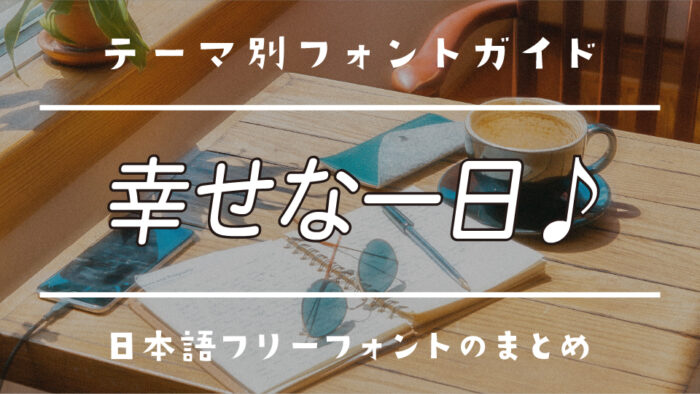
今回は、あたたかくて優しい気持ちになれる最近流行っている「幸せな一日」フォントな日本語フリーフォントをご紹介します。
Vlog風の映像やエモい字幕テキストにぴったりなフォントとして人気が高まっている「幸せな一日」フォントは、まるくて素直な印象の丸ゴシック体。ちょっとした日常の尊さや、心がじんわりとする瞬間を表現する際にぴったりあフォントです。
今回は、そんな「幸せな一日」に似ている近しい、やさしくてナチュラルな日本語フリーフォントをピックアップしました。動画制作やSNS投稿、写真加工のデザインにぜひ取り入れてみてください。
SNSでも話題!「幸せな一日」な字幕風日本語フリーフォント
「幸せな一日」フォントは、EPIKという写真加工アプリ内にある、『幸せな一日』というフォントです。
以下のサンプル画像は本記事で紹介している一部ですが、「幸せな一日」風にぴったりな可愛らしい字幕風フォントをまとめてみました。
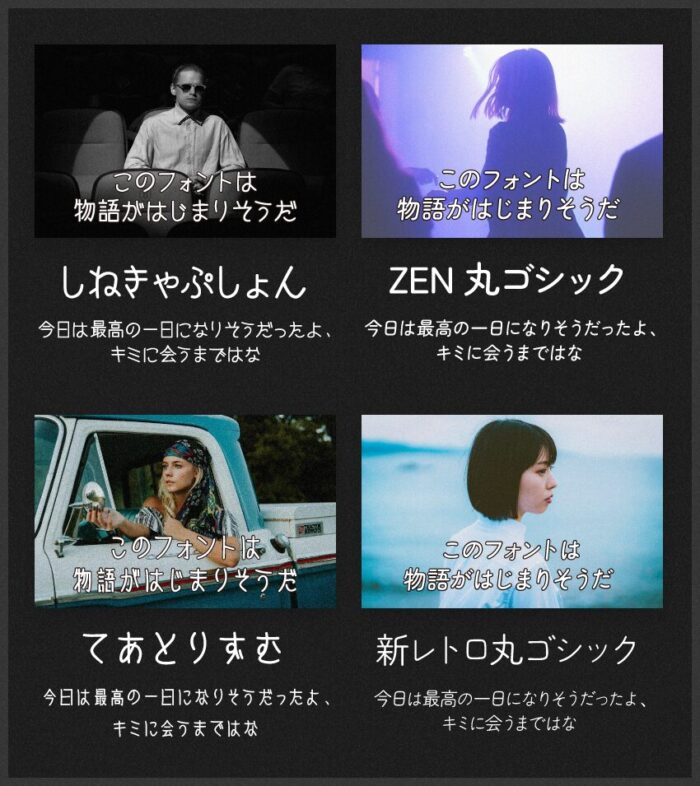
新レトロ丸ゴシック
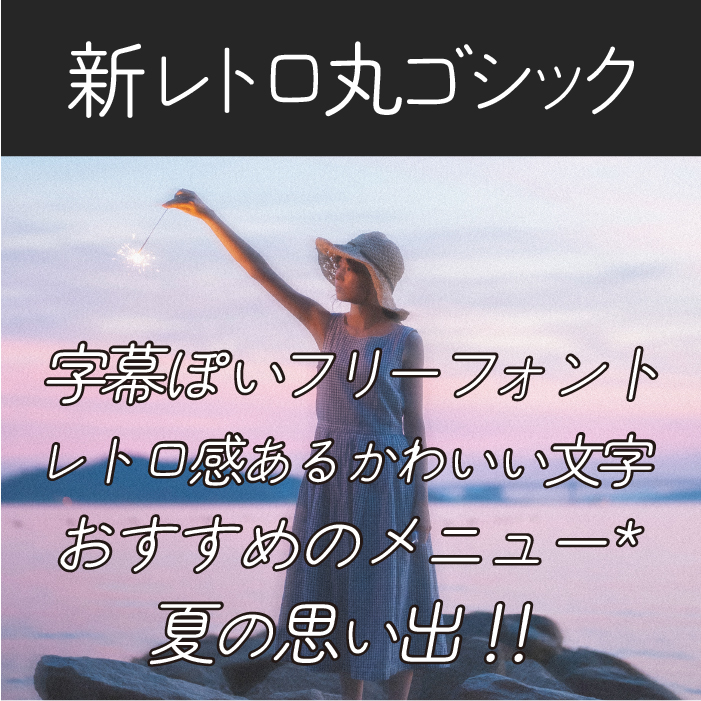
新レトロ丸ゴシックは、写植時代に使われていた丸ゴシックを参考に作られたレトロな表情のあるフォントです。
少し古い洋画のような字幕っぽさのレトロ感が可愛らしいフォントです。
小杉丸
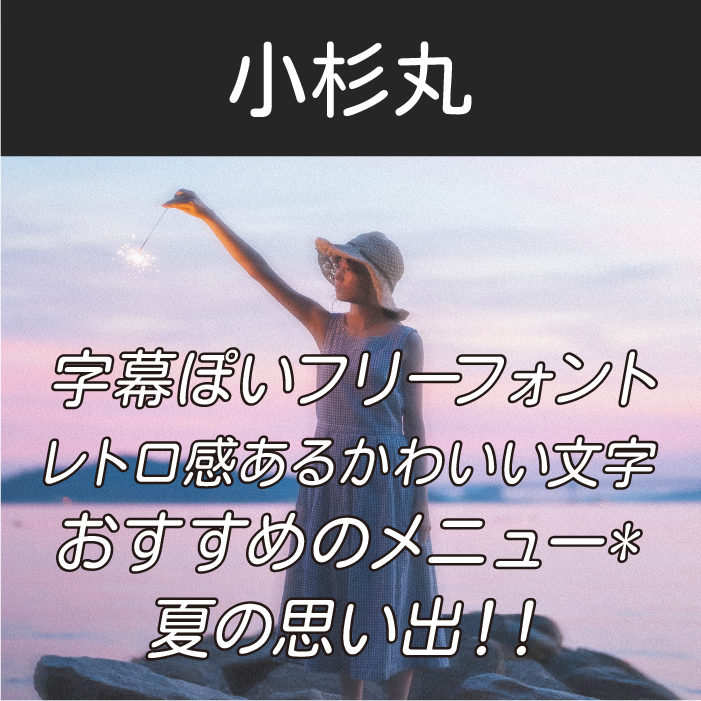
小杉丸(Kosugi Maru)フォントは、フォントメーカーモトヤが開発した高い可読性をもつ丸ゴシック体フォントです。
ZEN丸ゴシック
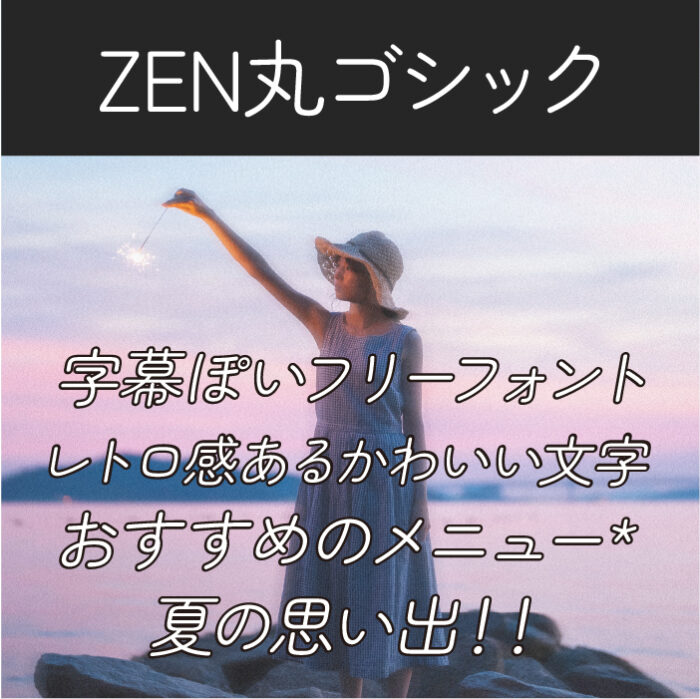
ZEN丸ゴシックフォントは、ナチュラルな印象でこぶりなかな文字が特徴的な丸ゴシック体のフォントです。ウェイトも3種類揃っているのも嬉しいポイントです。
キウイ丸
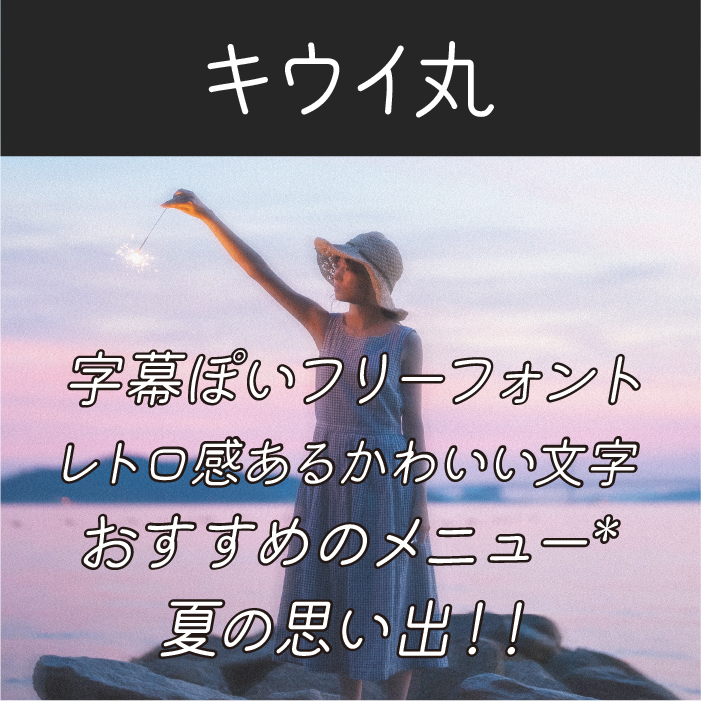
キウイ丸(Kiwi Maru)フォントは、丸みが可愛い丸ゴシック系フォントです。「幸せな一日」フォントにもある丸みが近しい雰囲気があり、とっても素敵なフォントです。
しねきゃぷしょん
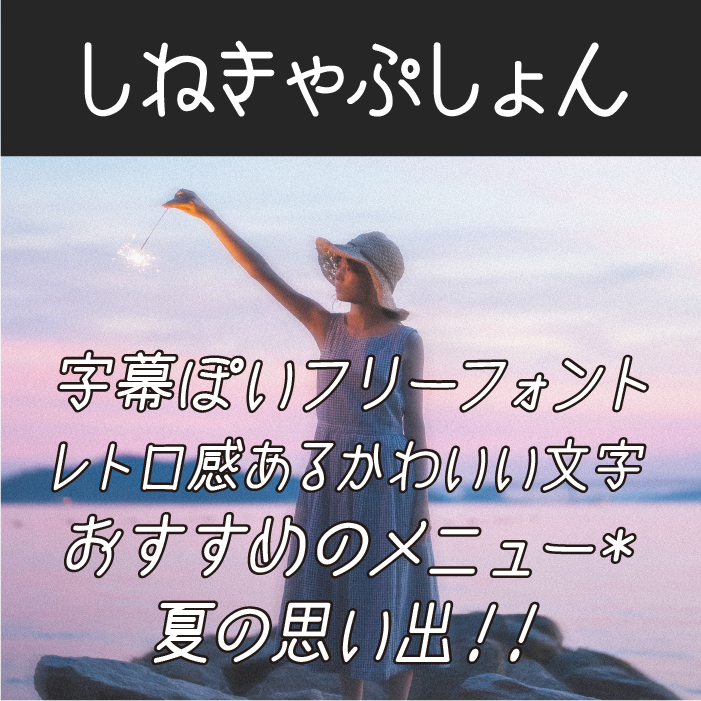
「しねきゃぷしょん」フォントは、映画で使われているの日本語字幕データをもとに作成された、映画の字幕のようなフォントです。
てあとりずむ
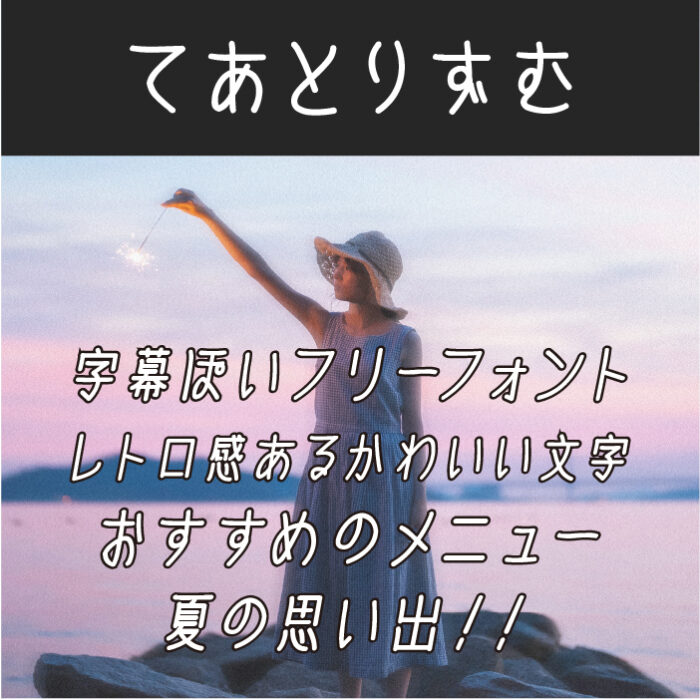
てあとりずむフォントは、優しい印象の手書き風の映画の字幕フォントです。「幸せな一日」フォントの丸ゴシックとは少し違った印象ですが、洋画の字幕のような世界観をもつフォントです。